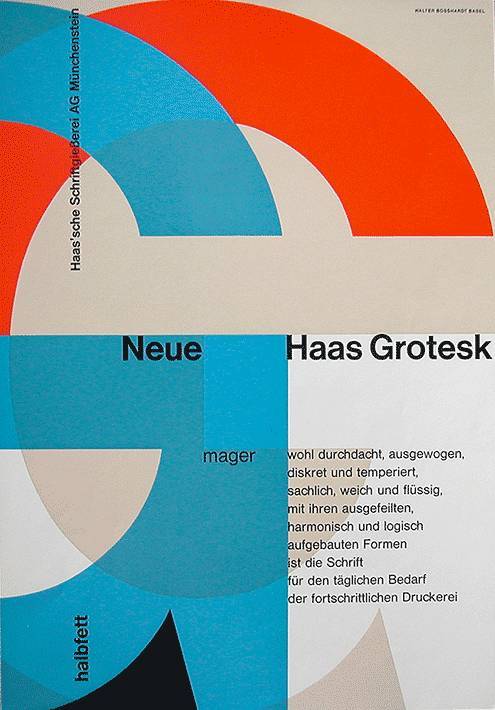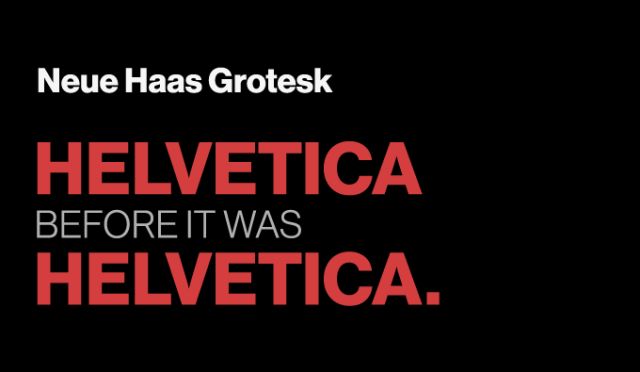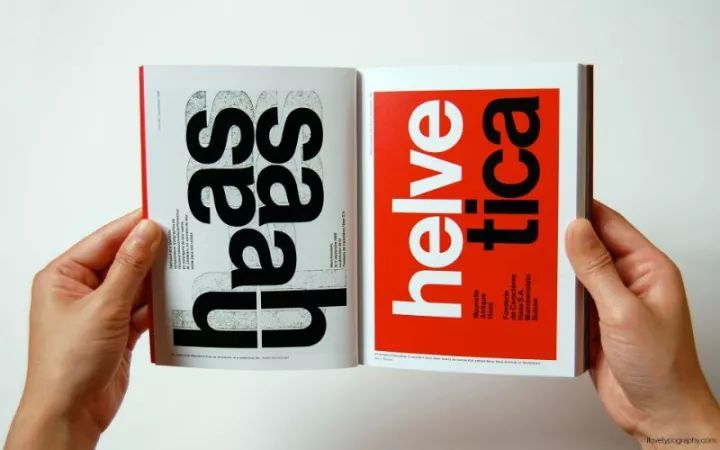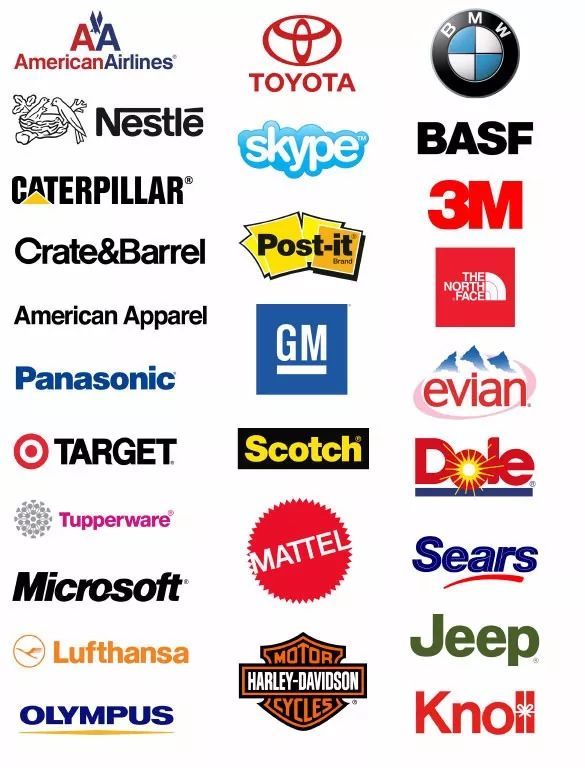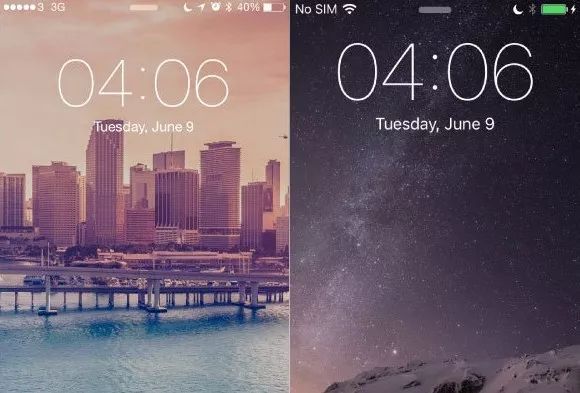
哪款是世界上最厉害的字体?
有人的地方就有江湖,字体也不例外,品牌Logo、宣传海报、地铁广告、网站App…我们的生活早已被字体包围。简单的字体背后是激烈的角逐甚至尔虞我诈,字体的世界比你想象得还要复杂。
哪款是世界上最厉害的字体?我说了不算,由你决定!
「字体江湖」第一期我们请来了Helvetica,苹果、宝马、无印良品、英特尔、三星、松下电器、汉莎航空、雀巢、Jeep等各大世界级知名品牌都不约而同选择它作为Logo,缔造了一个时代的传奇字体。花三分钟看完,你是否愿意为它投上一票?
时势造英雄
Helvetica诞生于20世纪五六十年代的瑞士,那时刚刚结束二战噩梦的欧洲陷入一种迷惘的状态。瑞士作为二战中的中立国简直是超脱一般的存在,其盛行的国际主义风格也广受欧洲各国追捧,Helvetica正是顺应时代趋势而生。
在Helvetica诞生之前,欧洲卖得最好的字体是由柏林字体公司柏涛德推出的Akzidenz Grotesk。现在用电脑下个字体又快又便宜,但当时还使用金属活字印刷的方式,设计一套字体贵的吓人,差不多相当于两辆甲壳虫汽车的价格。可见Akzidenz Grotesk是多有钱!
这时候Helvetica的两位爸爸要搞事了。
1955年,瑞士哈斯铸字厂的主理人爱德怀德.霍夫曼眼瞅着自己公司的字体越来越没市场,再这样下去关门了咋办,决心设计一款和Akzidenz Grotesk相抗衡的无衬线字体。
无衬线体(sans-serif)就是字母没有脚的字体。
爱德怀德.霍夫曼&哈斯铸字厂的车间
他找到当时身兼销售&设计的马克斯.米耶丁格,看人的眼光还是很准的!马克斯.米耶丁格既了解市场,又极具设计才华,立刻选择迎合现代主义。
马克斯.米耶丁格
直至1956年,他和霍夫曼终于设计出一款新的字体“New Haas Grotesk”,缩短了字母之间的间距,这在当时绝对是开创性的举措,事实证明和现代主义更配哦,简洁大方、可读性更强。
憋了一个大招在1957年“平面57”博览会上正式推出,这款顺应时代主流的无衬线字体立刻吸引了各大企业主的注意,源源不断的订单,估计霍夫曼做梦都能笑出来吧?
为什么叫Helvetica?
毕竟我本来叫“New Haas Grotesk”,但当时New Haas Grotesk虽然在瑞士小有名气,在国际上还没打响名号,名字这么长又难记,不利于国际化发展啊。
于是哈斯铸字厂的德国母公司Stempel说:“要不我们给它改个名吧,你们觉得Helvetia(即为拉丁文‘瑞士’)怎么样?”
霍夫曼跳出来表示反对,说好的国际化取一个国家的名字算怎么回事?最终这款字体定为“Helvetica”,延续了60多年之久。
看来有个好名字还是很重要的!在Stempel爸爸的支持下,Helvetica在国际上顺风顺水,当然主要还是字体给力。
我们知道设计一套字体家族有多贵,买一套当然也不便宜,可能当时有钱人都是这么显摆的:又出了最新一套字体,赶紧下手买了…?
Helvetica横扫字体领域的原因在于一点都不讲究,实用性特别强,一眼看去毫无特色,却能流畅自如地运用在各个场景领域。它最大的特点就是圆滑流畅的中性感、阅读体验超级好,也代表了瑞士给人一如既往中立的老好人形象。
大公司都爱它
在20世纪六七十年代,Helvetica几乎横扫全世界使用拉丁字母的国家。1962年,德国平面设计大师奥托.艾舍在为汉莎航空公司设计新Logo时,果断选择了Helvetica,就此一炮而红。
汉莎航空
跨国企业的名人效应把Helvetica字体带到了全世界,直到今天有数百家跨国企业都直接采用Helvetica作为企业标识。
比如美洲航空、宝马、英特尔、无印良品、摩托罗拉、丰田、三星…他们认为这种中性简约有力的字体最能代表企业正直正面的形象。
难道不是因为性价比高吗
而到了电子时代,1985年苹果将Helvetica装入电脑系统软件中,更是以爆炸性的速度在世界范围内传播开来。
Helvetica一直是苹果官方系统自带的字体,直到2015年iOS9弃用Helvetica,使用自家San Francisco字体还引起了大规模反对的声音。
锁屏界面对比,左为Helvetica,右为San Francisco字体
就连酷到不行的川久保玲都采用Helvetica作为Comme des Garçons 和 American Apparel品牌的Logo,可见其经久不衰的平凡魅力。
川久保玲
除了这些企业品牌,政府也超喜欢这款字体,在许多公共部门和公共设施都采用Helvetica。
特别是在20世纪七十年代,设计师玛西莫.维格尼利为纽约地铁设计标识系统和地图,它开始陆续垄断所有政府部门的标识…
上头有人真好,羡慕?
纽约地铁站
而纽约现代艺术博物馆也将其列入最早的馆藏字体,这是极高的荣誉,如果字体会说话,可能会高兴得尬舞…
2007年纽约艺术博物馆举办Helvetica50周年纪念展。
Helvetica走过半个多世纪之久,跨越了活字印刷到互联网信息时代,历经现代主义、后现代主义、绿色有机主义等不同时期的设计风格,却以其惊人的适应性顺应每个潮流的更替,让全世界的设计师、企业家、字体爱好者…都为它所着迷。
甚至纽约设计师Albert Son创立了一个以Helvetica命名的品牌。
如空气一般的存在
就算我们不了解Helvetica,也不得不承认它已与我们的生活紧密联结在一起。它如此平凡却又如此真实简单,中性简洁的表现力让Helvetica看上去冰冷而缺乏感情,然而这正是我们爱它的理由。
每个人都能透过字体透过文字进行自我解读,而不会在视觉上陷入字体所编织的狂想中。但是有多少人爱它,就有多少人讨厌它,有人说:Helvetica就像一个普通到淹没在人群里的人对你say hello,而你对此毫无印象…当街头巷尾都装饰着Helvetica字体时,又有什么更多的惊喜?
在纪录片《Helvetica》中导演邀请了众多位设计界大师表达自己对Helvetica的看法,德国Erik Spikermann很直白地说:“谁知道呢,为什么坏品味满大街都是?”
老铁,扎心了?
但本身一个字体被拍成纪录片就是传奇,盛名之下必定会有非议,无处不在的地方我们看到Helvetica,它看起来一点都不高级、有点圆滑过于温润,但我们知道它就在那里,离不开它。